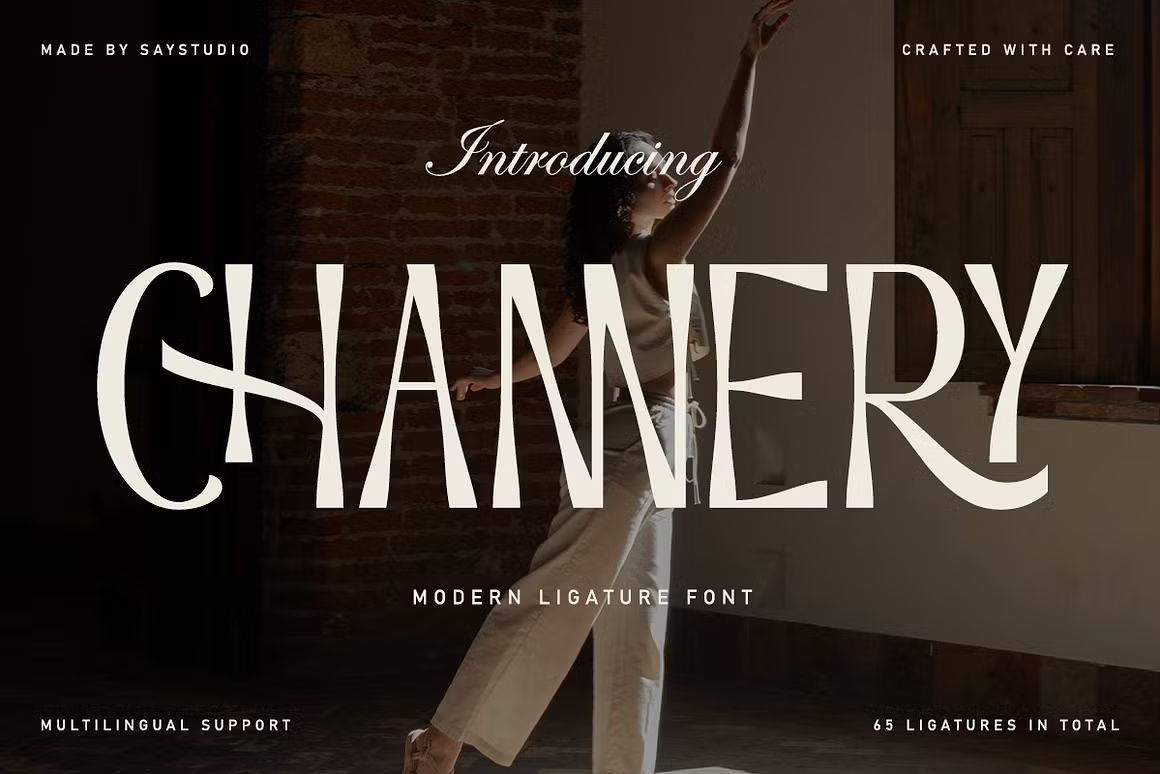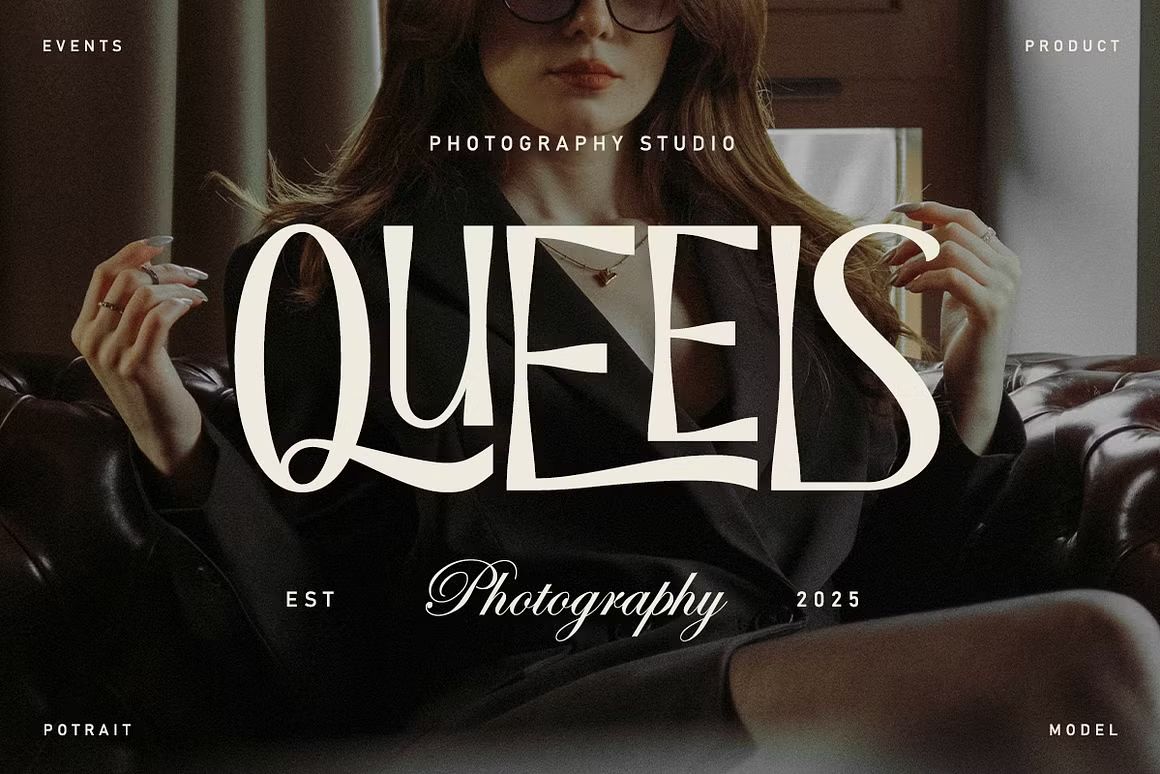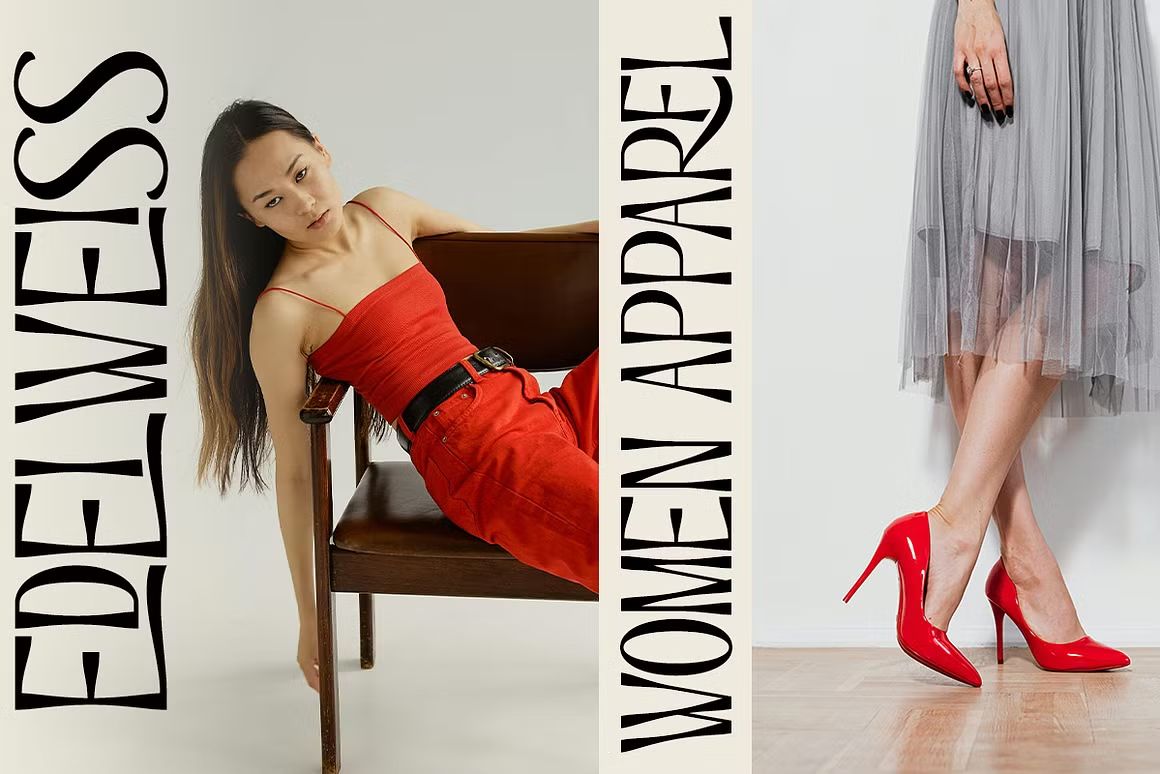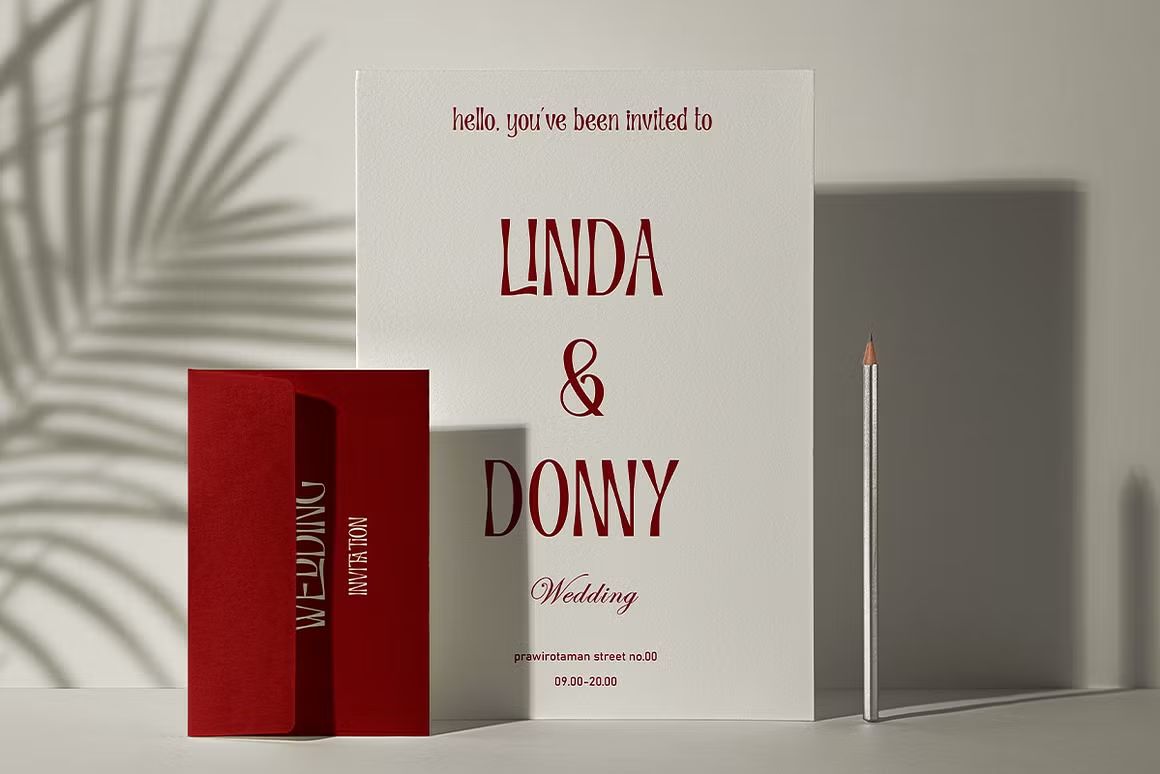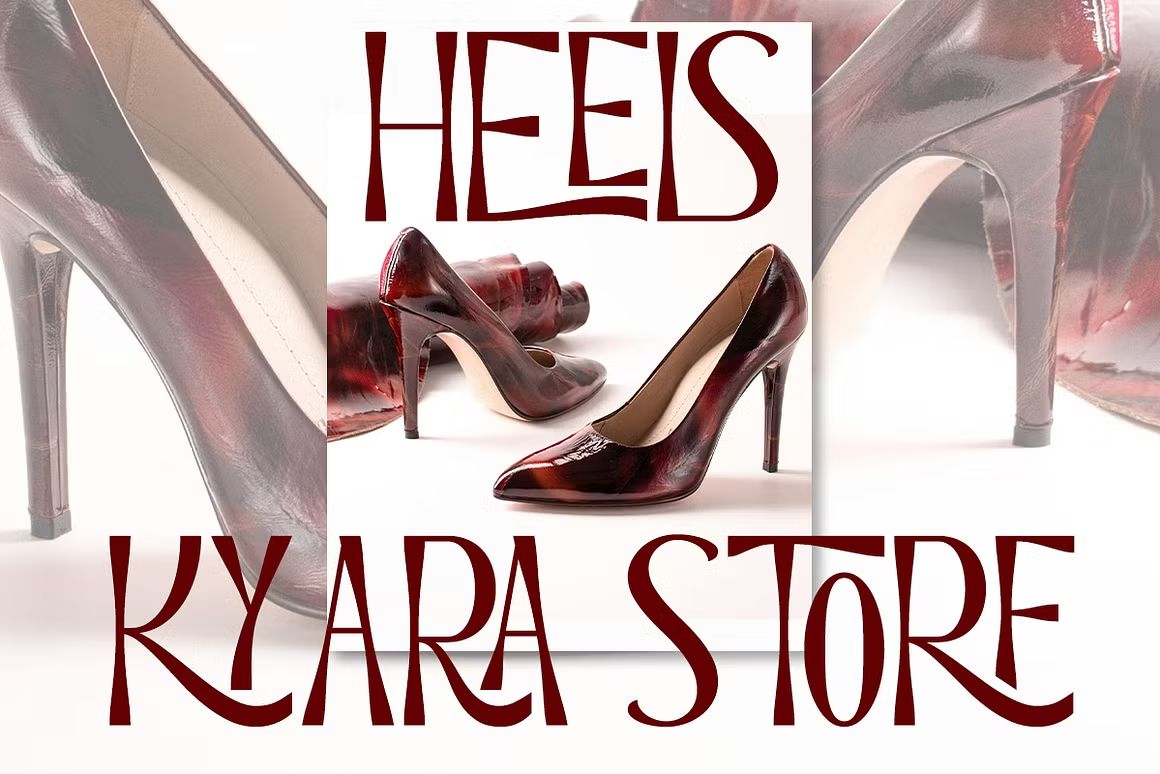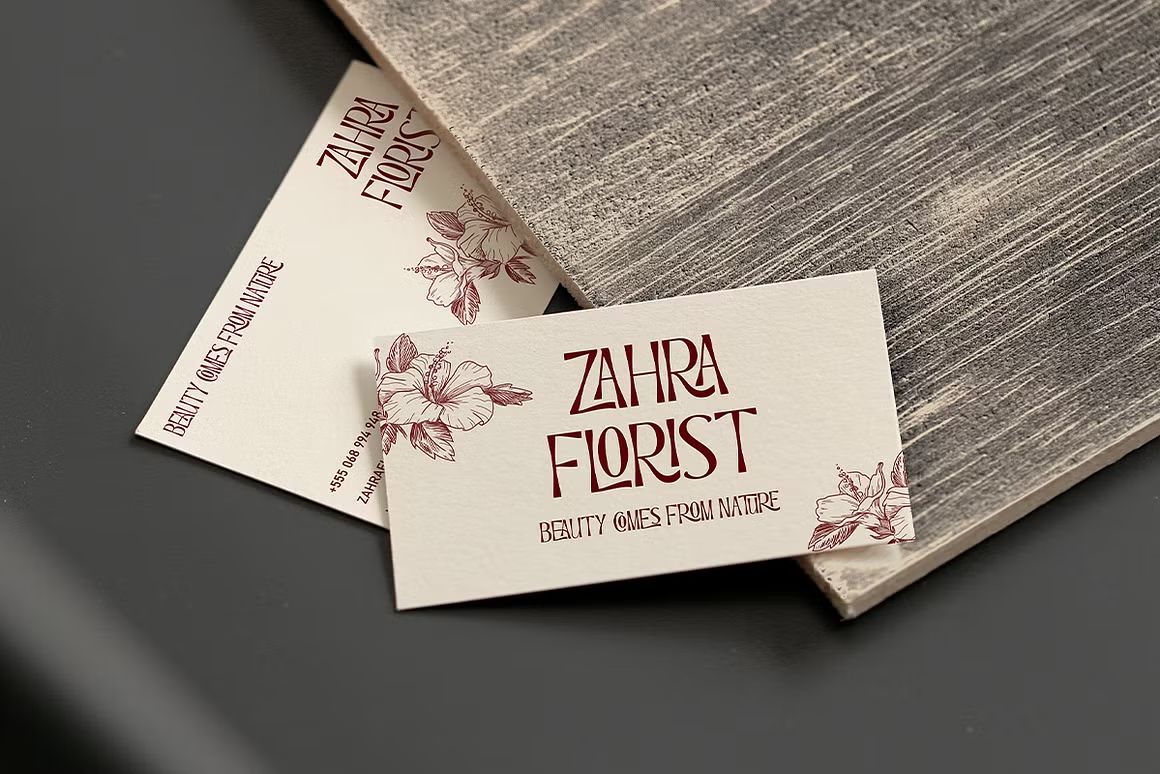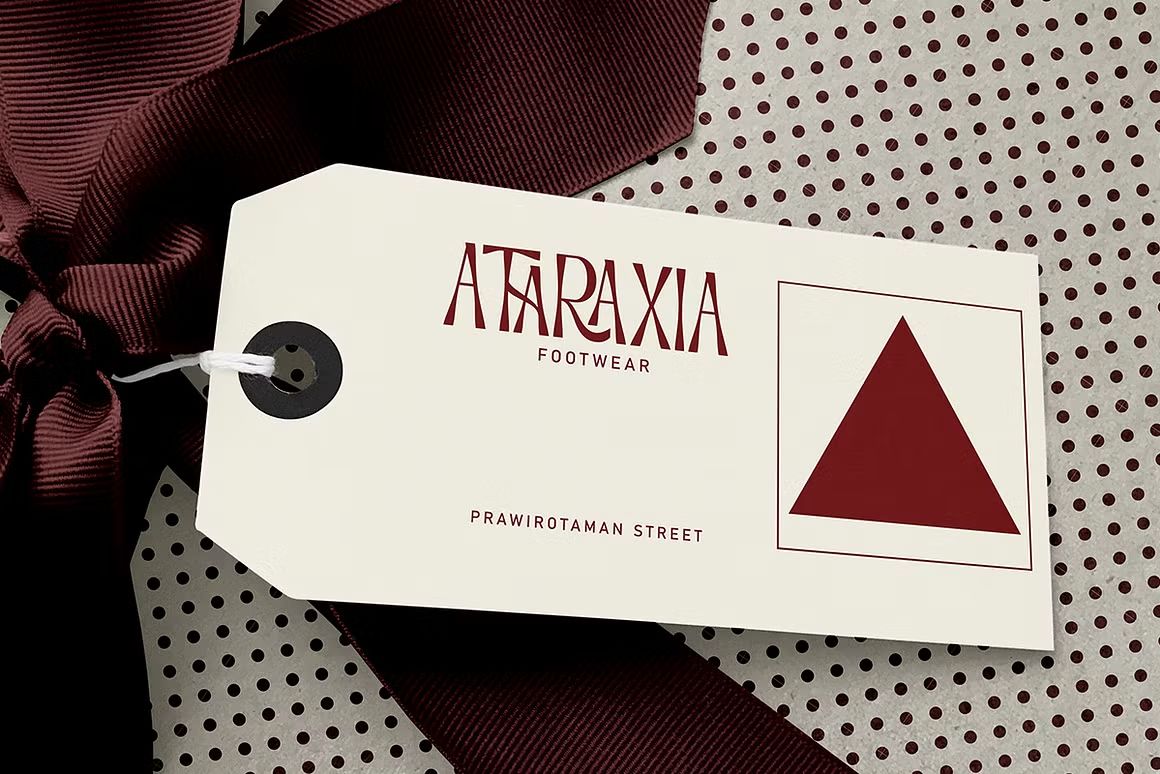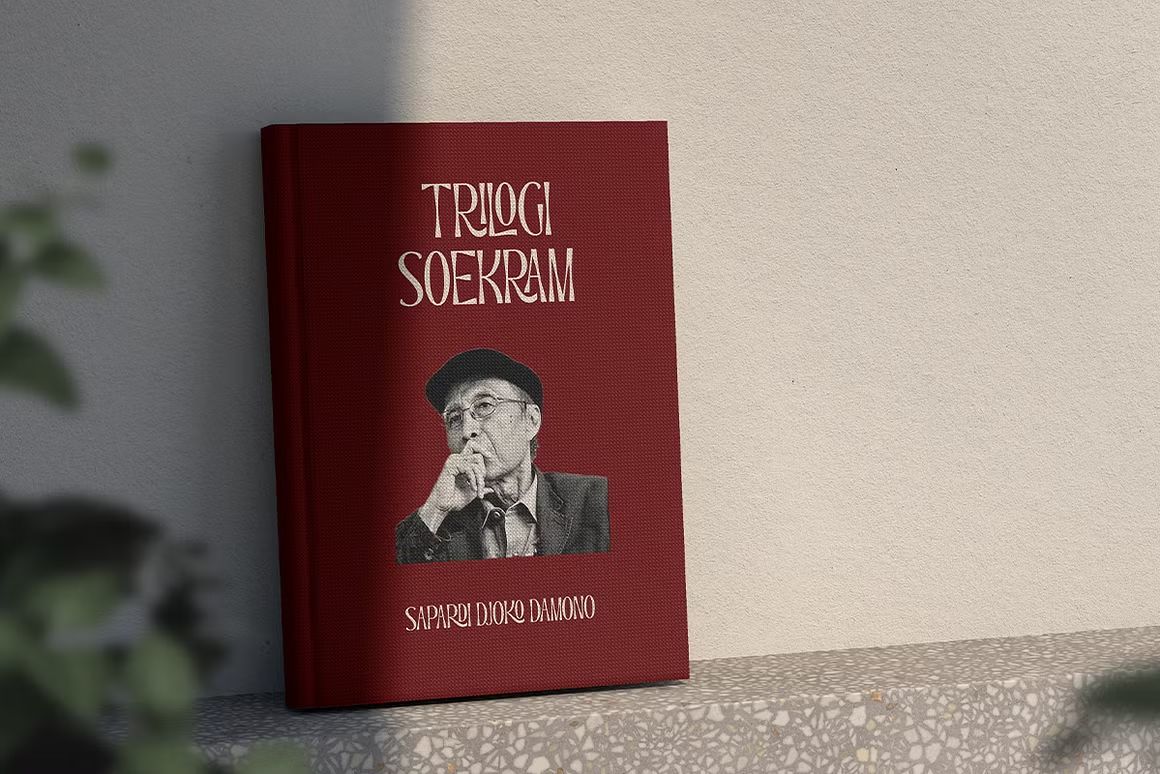
Channery – Sans Serif Font
Channery adalah font sans serif modern dengan sentuhan lembut dan elegan. Dirancang dengan bentuk huruf yang ramping dan proporsi seimbang, Channery cocok untuk branding feminin, desain editorial, kemasan produk, dan media sosial. Font ini menghadirkan nuansa profesional yang tetap hangat dan bersahabat, ideal untuk berbagai gaya visual yang bersih dan kontemporer.
• Sans serif ramping dengan nuansa elegan dan modern
• Cocok untuk branding, editorial, dan konten digital
• Termasuk huruf kapital, kecil, angka, dan simbol